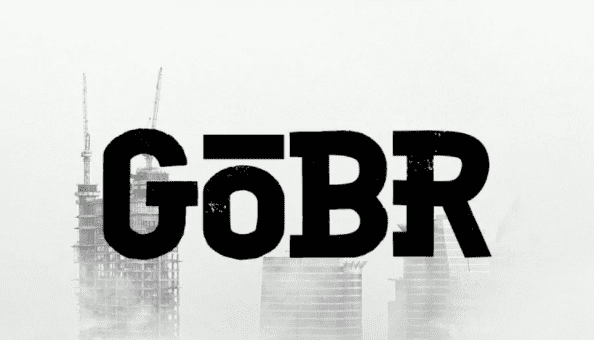
Название: Gobr Font (2021)
У этого шрифта сильное тело, но некоторые части гибкие с несимметричной дугой линии. Этот шрифт имеет немного Nois, его хорошо использовать для дизайна бренда одежды с уличной тематикой. Этот шрифт может быть использован для уличной культуры, скейтбордов, фресок, хип-хопа, рэпа и т.д.
Название: Gobr Font (2021)
У этого шрифта сильное тело, но некоторые части гибкие с несимметричной дугой линии. Этот шрифт имеет немного Nois, его хорошо использовать для дизайна бренда одежды с уличной тематикой. Этот шрифт может быть использован для уличной культуры, скейтбордов, фресок, хип-хопа, рэпа и т.д.